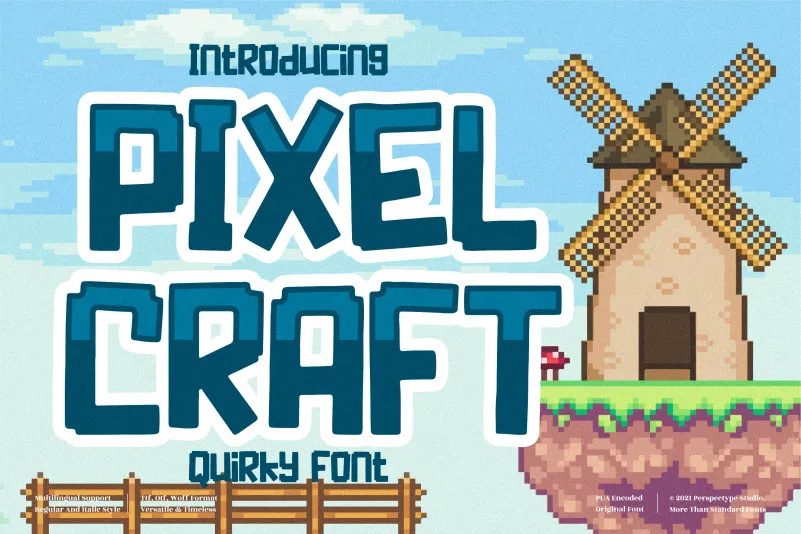
A fonte Pixel Craft é uma elegante escolha para qualquer projeto que exija um toque divertido e autêntico. Essa fonte display possui um visual encantador, repleto de graça e originalidade, perfeitamente projetada para destacar atividades infantis ou trabalho escolar. Seu design atemporal se destaca em qualquer mídia digital, seja no web, impressão ou aplicativo móvel. Ideal para designers que desejam trazer um ar leve e engraçado a seus projetos, Pixel Craft é uma excelente opção para quem busca criatividade e conforto visual. Com certeza será o destaque em qualquer projeto infantil ou escolar que você quiser dar vida à!